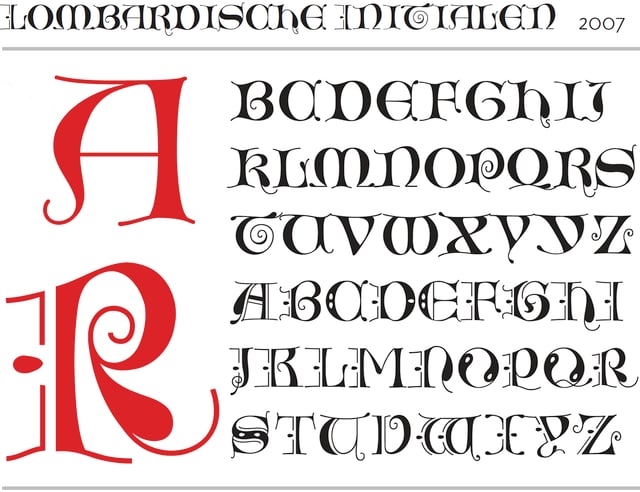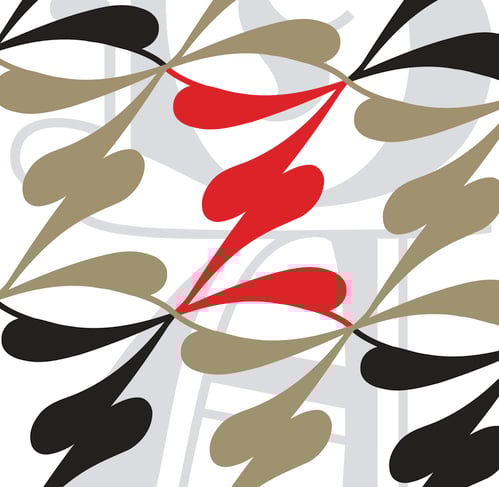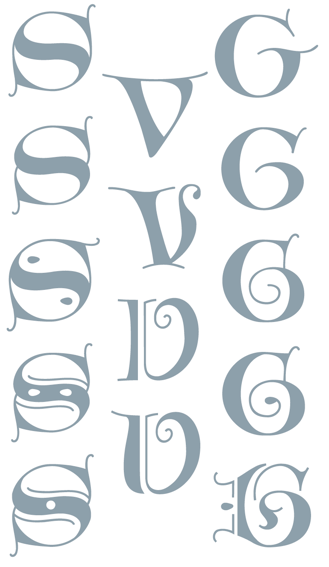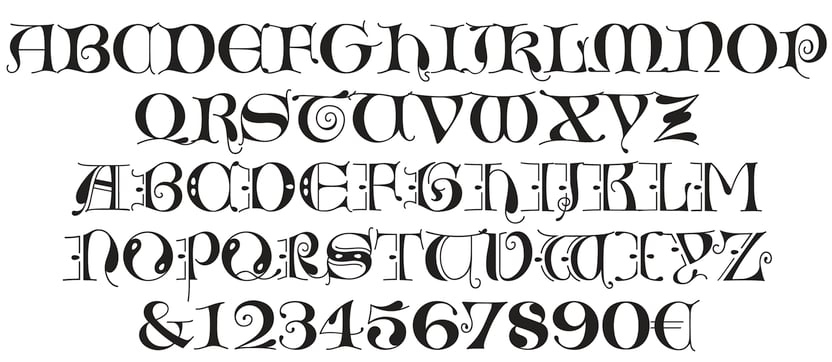
Lombardische Initialen
Die Lombardischen Initialen dienten im Mittelalter als Initialen in Handschriften. Auch in frühen Druckwerken der Renaissance, wie zum Beispiel in der Schedelschen Weltchronik aus dem Jahr 1493, wurden Lombardische Initialen zur Kenntlichmachung von Absätzen benutzt. Sie wurden manchmal auch für Inschriften verwendet, so zum Beispiel am Gotischen Münster in Schwäbisch Gmünd. Bei den Arbeiten an der Typografie für das »Badische Markgrafenfest« suchte ich solche Initialen und fand eine enorme Vielfalt in alten Büchern und Manuskripten. Die verfügbaren digitalen Fonts fand ich nicht befriedigend – und so entstanden »meine« Lombardischen Initialen. Die Vielfalt der Vorlagen könnte einen leicht dazu verleiten, endlos weiter zu zeichnen und immer neue Variationen zu entdecken.